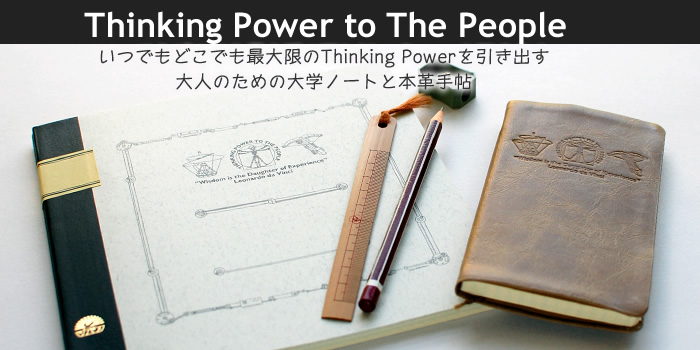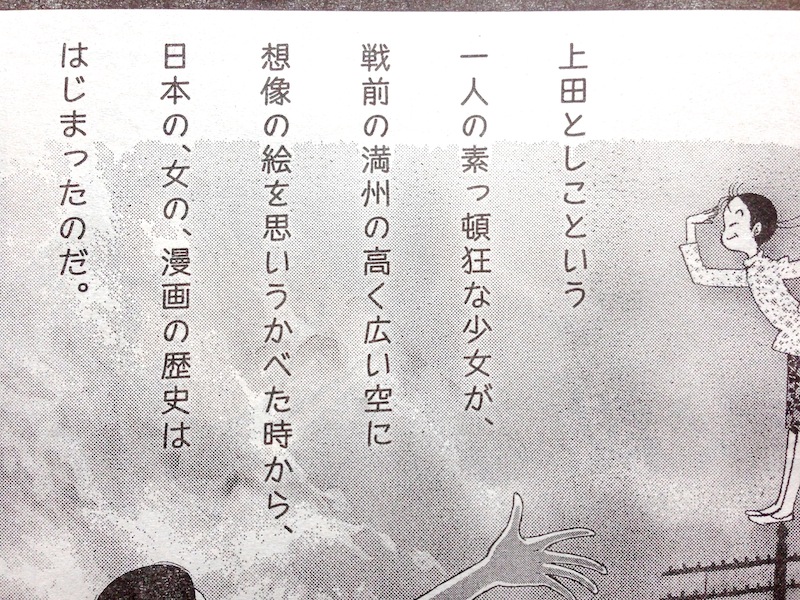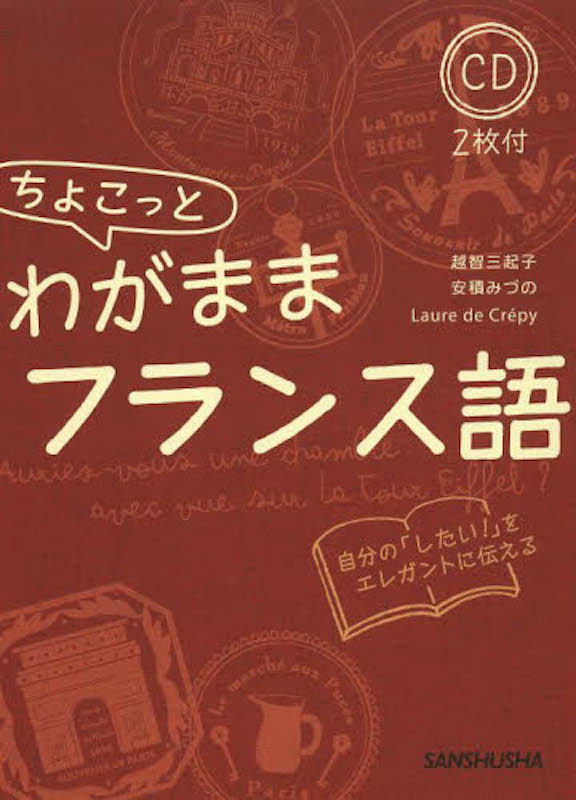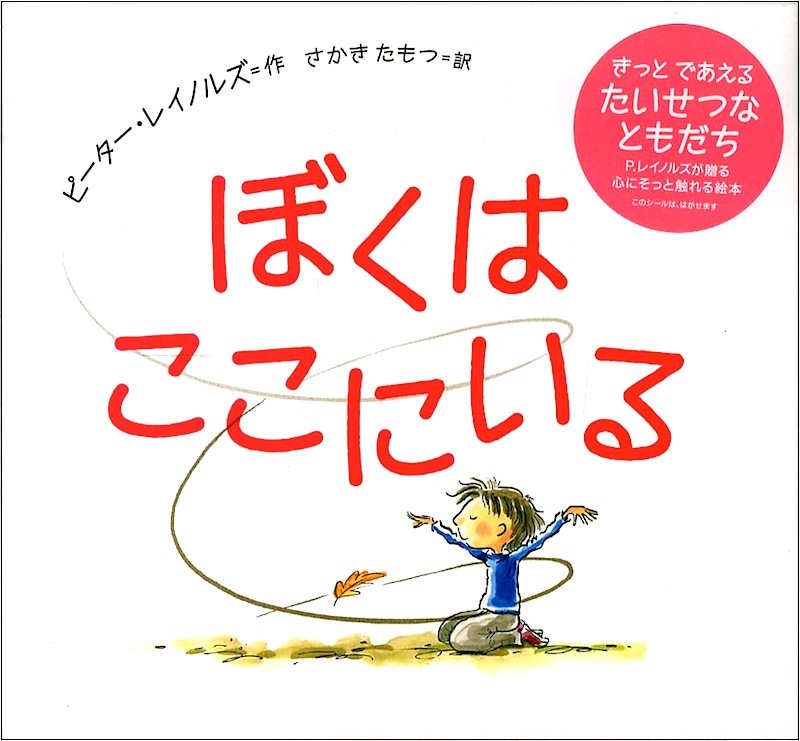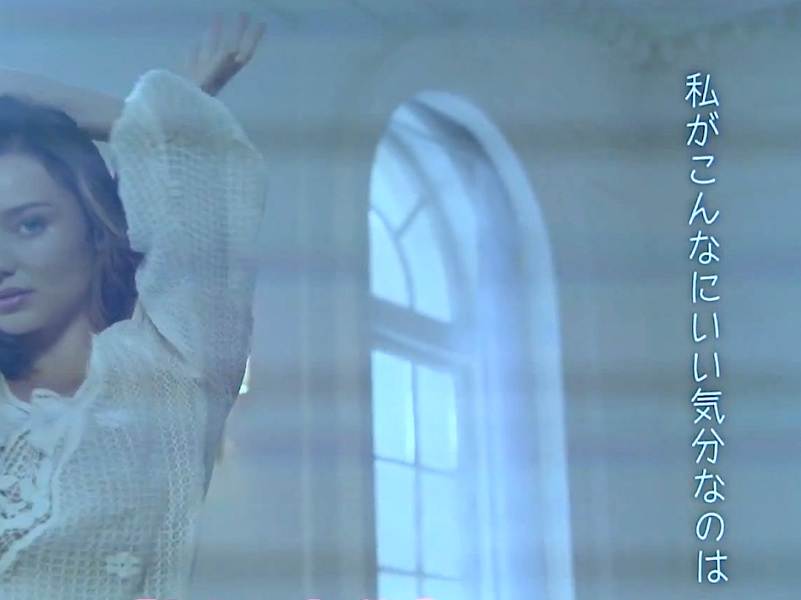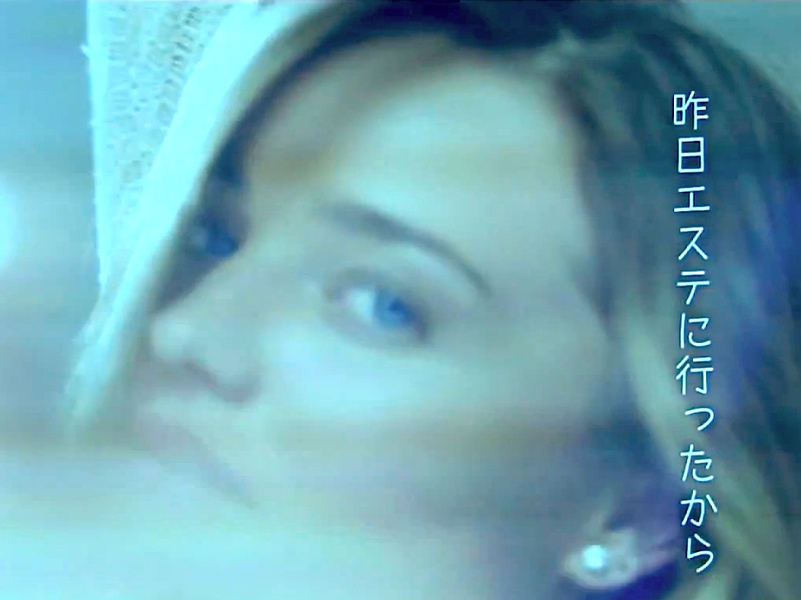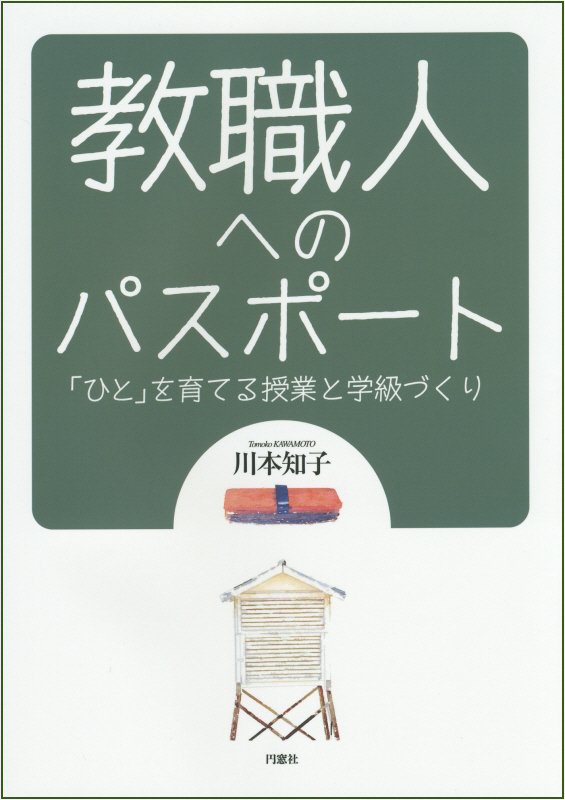
豆本  さとうゆたか  2016年7月18日(月) 11:51
書名:8月サイダー
著者:はばらあきよ
発行:オレンジ宇宙工場
さとうゆたか  2016年7月18日(月) 11:52 [修正]
本文もセプテンバー書体です。
JAL機内誌  suzu  2016年6月22日(水) 21:46
沖縄へ旅行中 JTA機内誌コーラルウェイ - 裏表紙に見つけました。
さとうゆたか  2016年6月22日(水) 21:56 [修正]
私は昨年、JALの機内誌でも見つけました。
この掲示板を下にスクロールして、2015年4月30日に掲載しております。
こぐまのクッキー  さとうゆたか  2008年4月29日(火) 17:07
絵本の表紙です。
書名:きょうはおたんじょうび
著者:ジュディス コッペン
訳者:東森プリン
出版社:アシェット婦人画報社
さとうゆたか  2008年4月29日(火) 17:09 [修正]
同じシリーズで、もう1点。
書名:大きくなりたい!
著者:ジュディス コッペン
訳者:久保玲子
出版社:アシェット婦人画報社
さとうゆたか  2016年2月15日(月) 11:01 [修正]
もう1点、ありました。
書名:キリンさんにキス
著者:ジュディス コッペン
訳者:久保玲子
出版社:アシェット婦人画報社
ドーナッツ店  さとうゆたか  2015年5月27日(水) 8:53
神戸に本店がある「はらドーナッツ」。
追加  さとうゆたか  2015年5月27日(水) 8:54 [修正]
こちらでは、品名と価格部分に。
さとうゆたか  2015年10月22日(木) 9:05 [修正]
追加です。
さとうゆたか  2015年10月22日(木) 9:06 [修正]
もう1点。
てなしも  2015年8月31日(月) 0:49  HP
日経BP社「看取りの技術」
図書館の新刊コーナーに置いてありました(セプテンバーL)。
さとうゆたか  2015年8月31日(月) 8:37 [修正]
書名:看取りの技術
著者:平方 眞
発行:日経BP社
デコもじでセプテンバー…  takumi  2015年8月23日(日) 2:44  HP
テレビCM  さとうゆたか  2015年5月23日(土) 8:10
エブリスタ小説大賞。
雑誌記事の見出し  さとうゆたか  2015年4月30日(木) 21:34
JALの機内誌、SKYWARD。
英字は等幅が使われている。
本の表紙  さとうゆたか  2015年4月19日(日) 15:57
書名:教職人へのパスポート
著者:川本知子
発行:円窓社、雲母書房